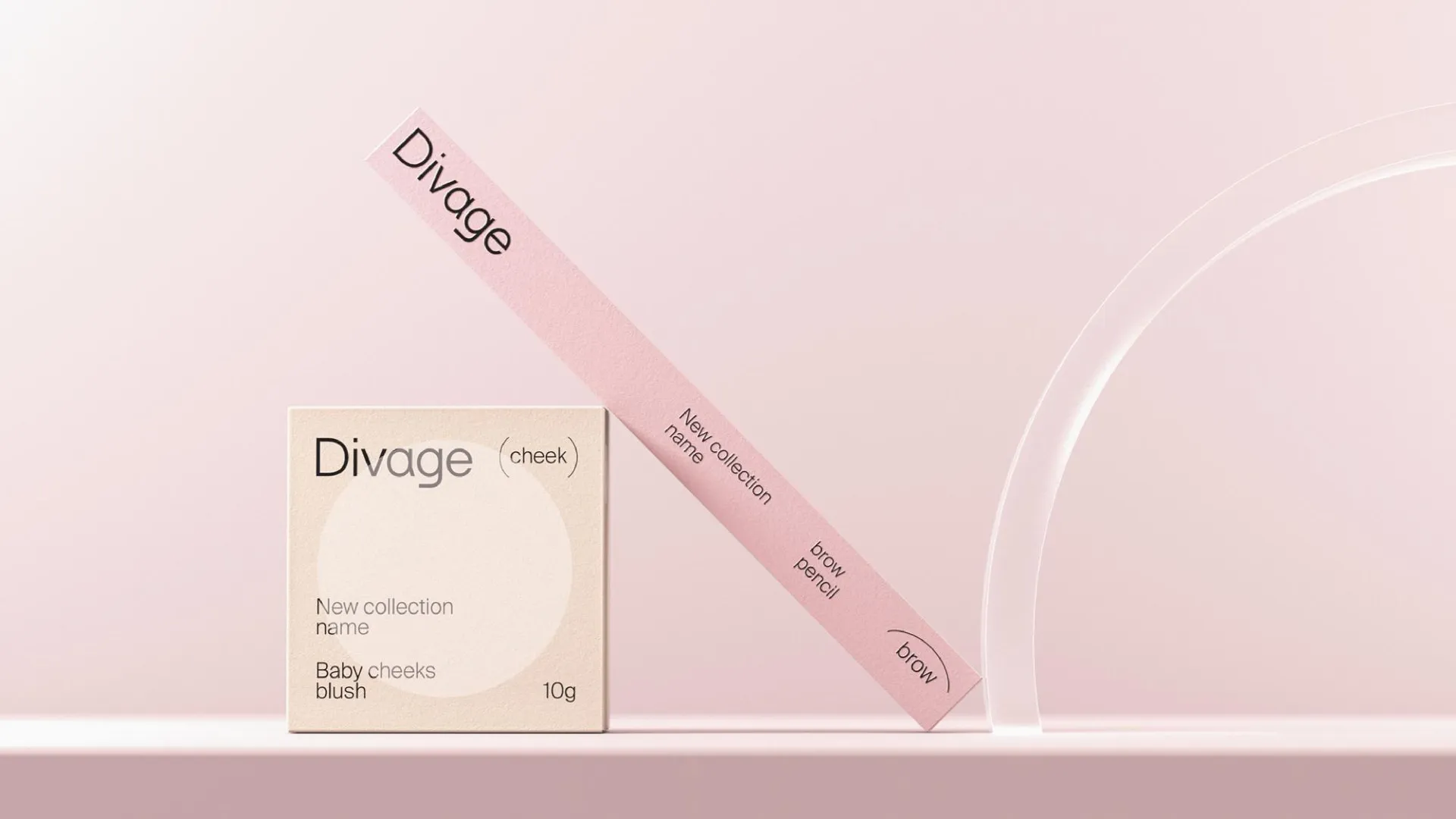
Шрифт в логотипе
Разработка логотипа требует тонкого понимания природы букв и умения связывать эмоциональный посыл бренда с графической формой. За два занятия вы освоите принципы создания собственного визуального инструментария, который позволит подбирать и адаптировать шрифтовые решения под конкретные запросы клиентов. Внутри разбираются технические параметры шрифта: пропорции, контраст и оптические компенсации, а также смысловые характеристики: как ритм, рифма и эмоциональный тон букв формируют характер логотипа. Обучение ориентировано на дизайнеров, желающих научиться осознанно управлять графикой. Итогом станет готовый логотип, созданный на основе учебных брифов, который можно добавить в портфолио.
- Параметры шрифта
- связь письма с современной формой буквы
- пропорции, графема, контраст
- распределение контраста
- взаимосвязи элементов букв
- базовые оптические компенсации
- Логотип
- шрифт и логотип, ритм и рифма
- смысловые характеристики
- эмоциональные характеристики
- проработка брифа на создание логотипа